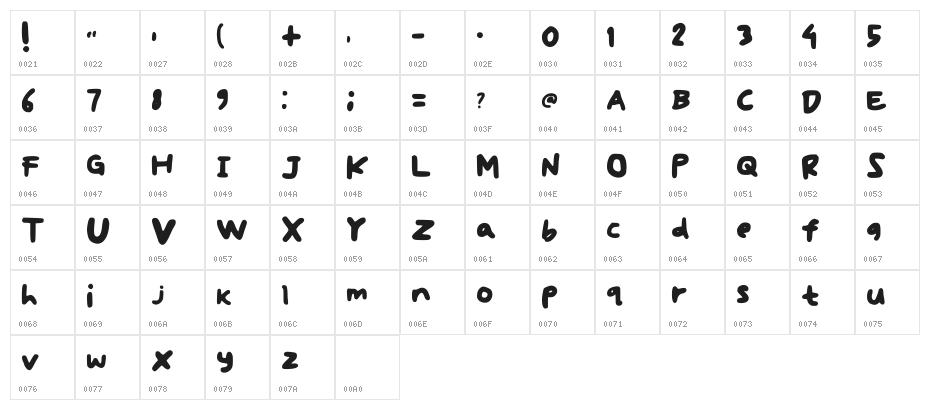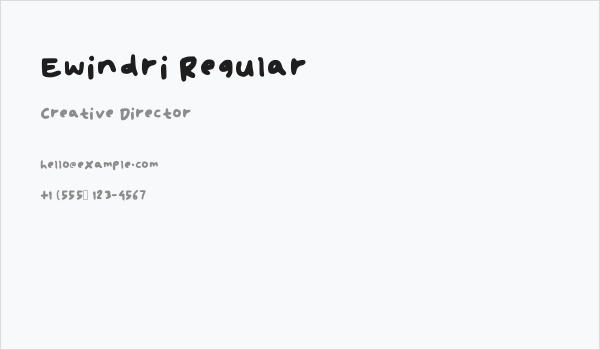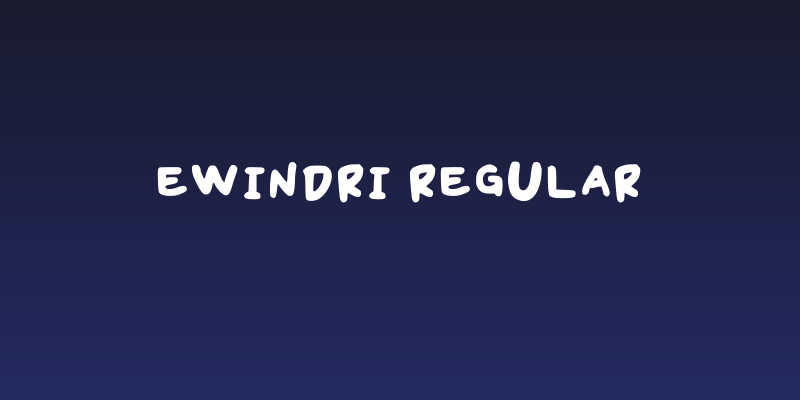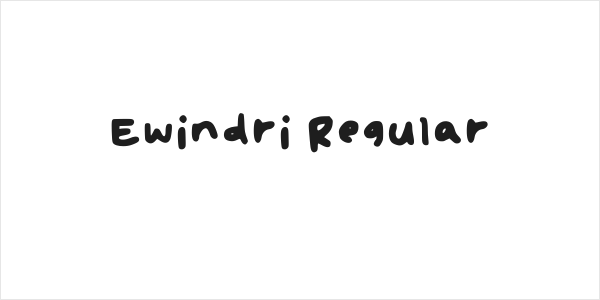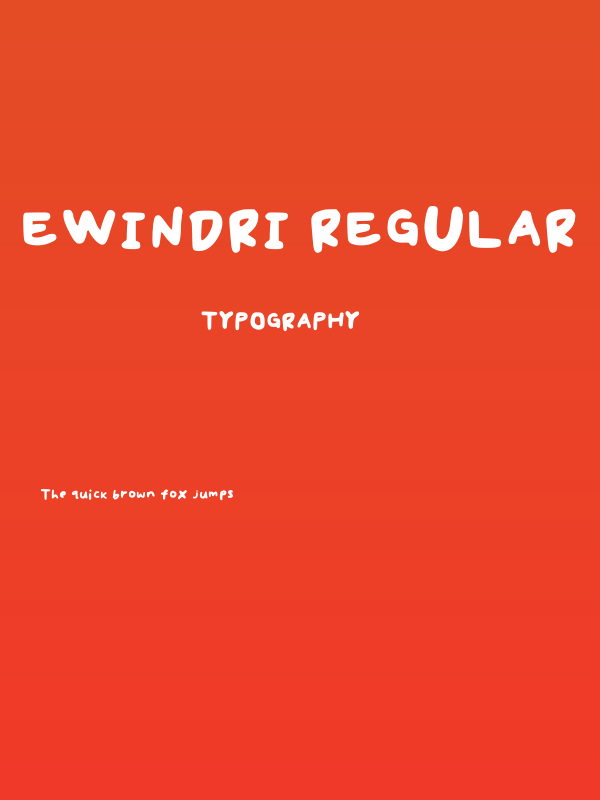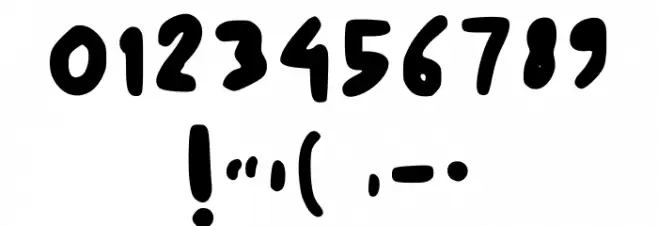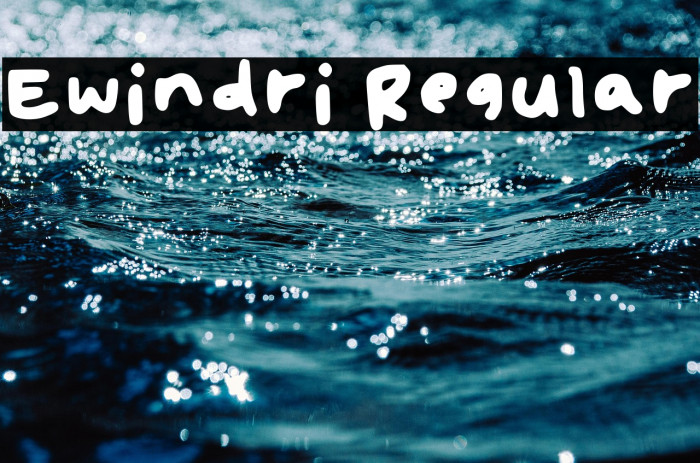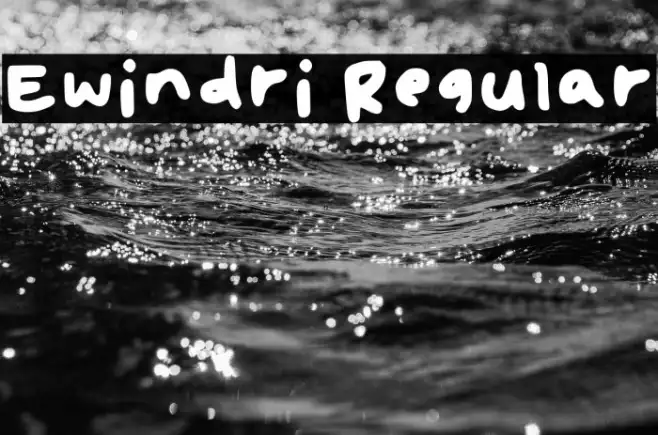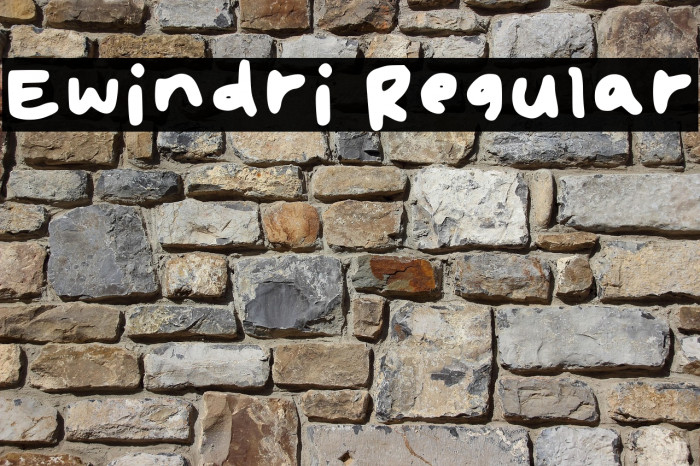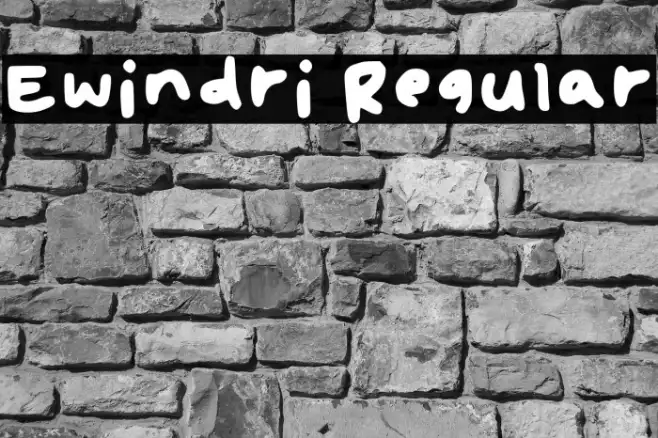
Ewindri Regular Font
| Gesamtstil | Casual, Playful |
| Anwendungsfall | Headlines, Logos, Informal Text |
| Vorgeschlagene Projekte | Ideal for children's books, casual branding, greeting cards, and playful social media graphics. |